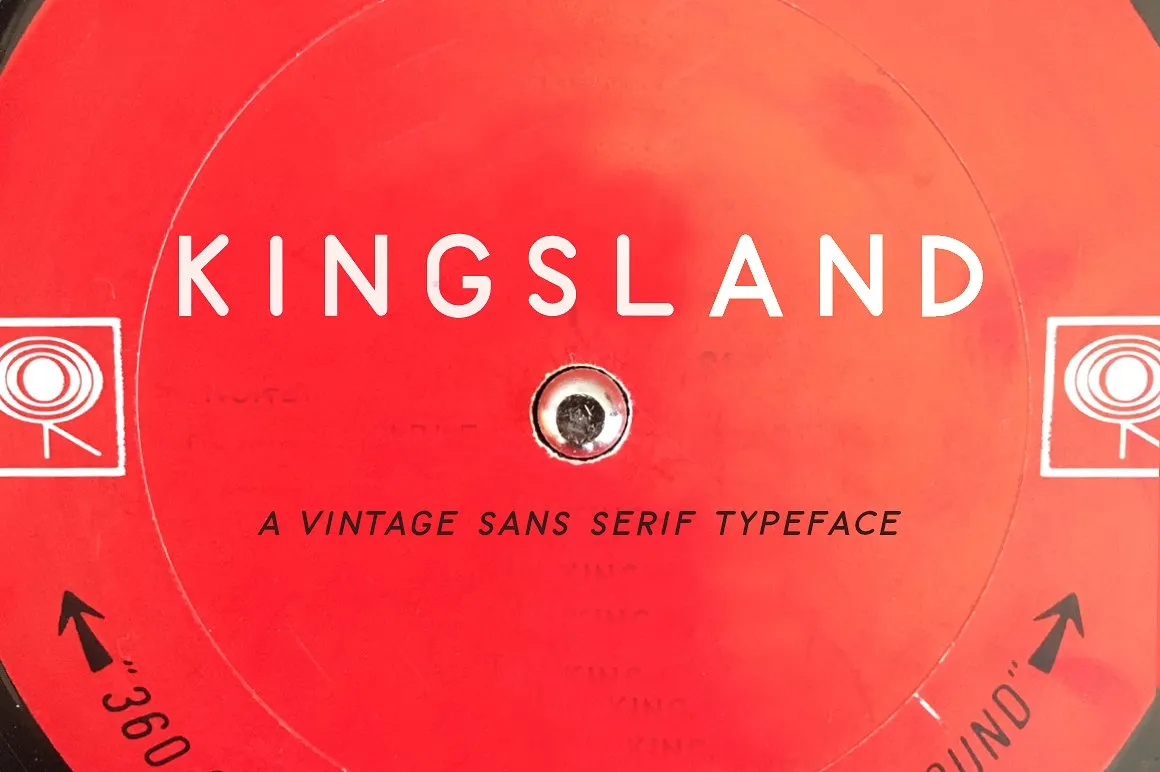
Kingsland Typeface – Fonte Grátis
Kingsland Typeface
Kingsland Typeface é uma elegante fonte de tipo sans serif criada por Jen Wagner Co., disponível gratuitamente para download na Creativemarket. Inspirado no velho disco do cantor Johnny Cash que estava em sua sala de estar, Kingsland oferece um visual vintage com letras em caixa alta e destaca-se como uma opção excepcional para projetos de tipografia, logotipos, sinalização, convites, marcações, sites e muito mais. Este tipo fantástico ganhou rapidamente a reputação entre os designers por seu charme único e simplicidade contemporânea. Seja você um estilista ou designer gráfico, Kingsland é uma excelente fonte para sua coleção, capaz de dar qualquer projeto um toque moderno sem perder o encanto clássico da escrita em letras caixa alta.